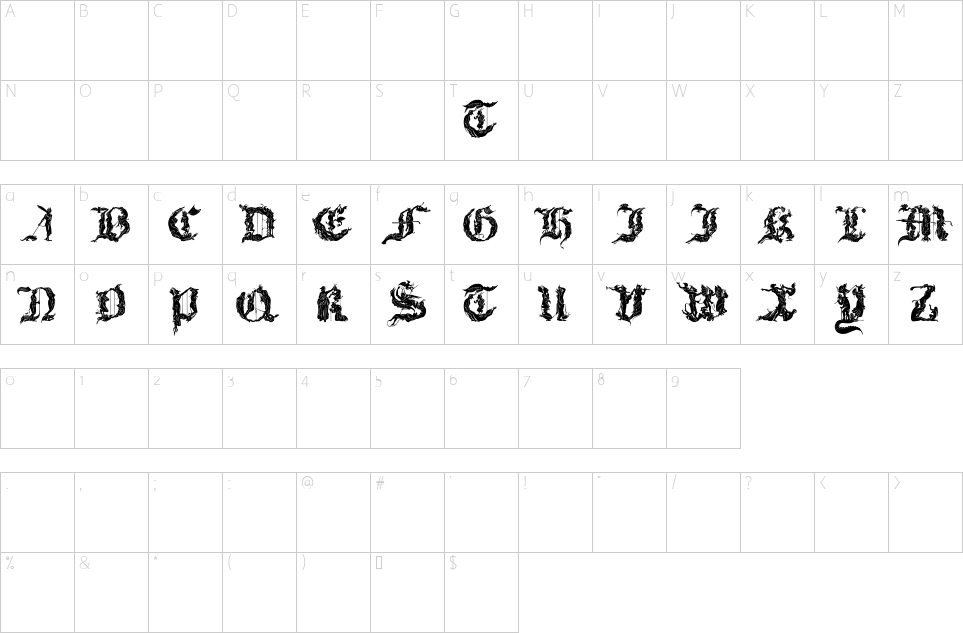
Diabolique Font
A Diabolique é uma fonte elegante e única que pode adicionar uma pitada de originalidade a qualquer projeto visual. Ela foi projetada pelo Jester Font Studio, e já foi baixada mais de 4279 vezes. Suas linhas curvas e detalhes delicados criam um estilo único que se destaca em layouts gráficos como infográficos, design editorial ou arte digital. A Diabolique é uma ótima opção para designers procurando por algo inovador e divertido, sem abrir mão da legibilidade. Baixe-a gratuitamente e veja onde ela pode trazer alegria ao seu trabalho.